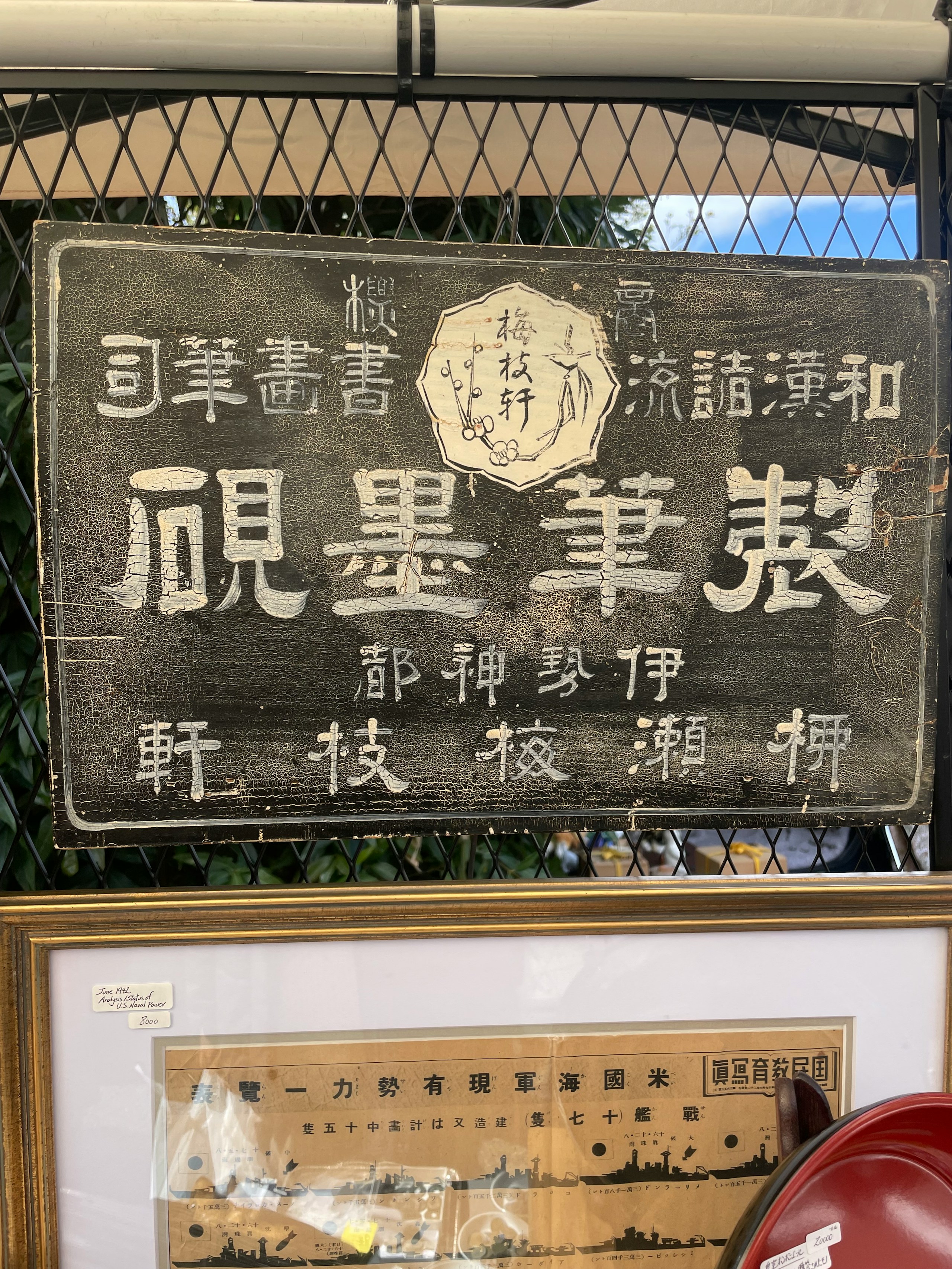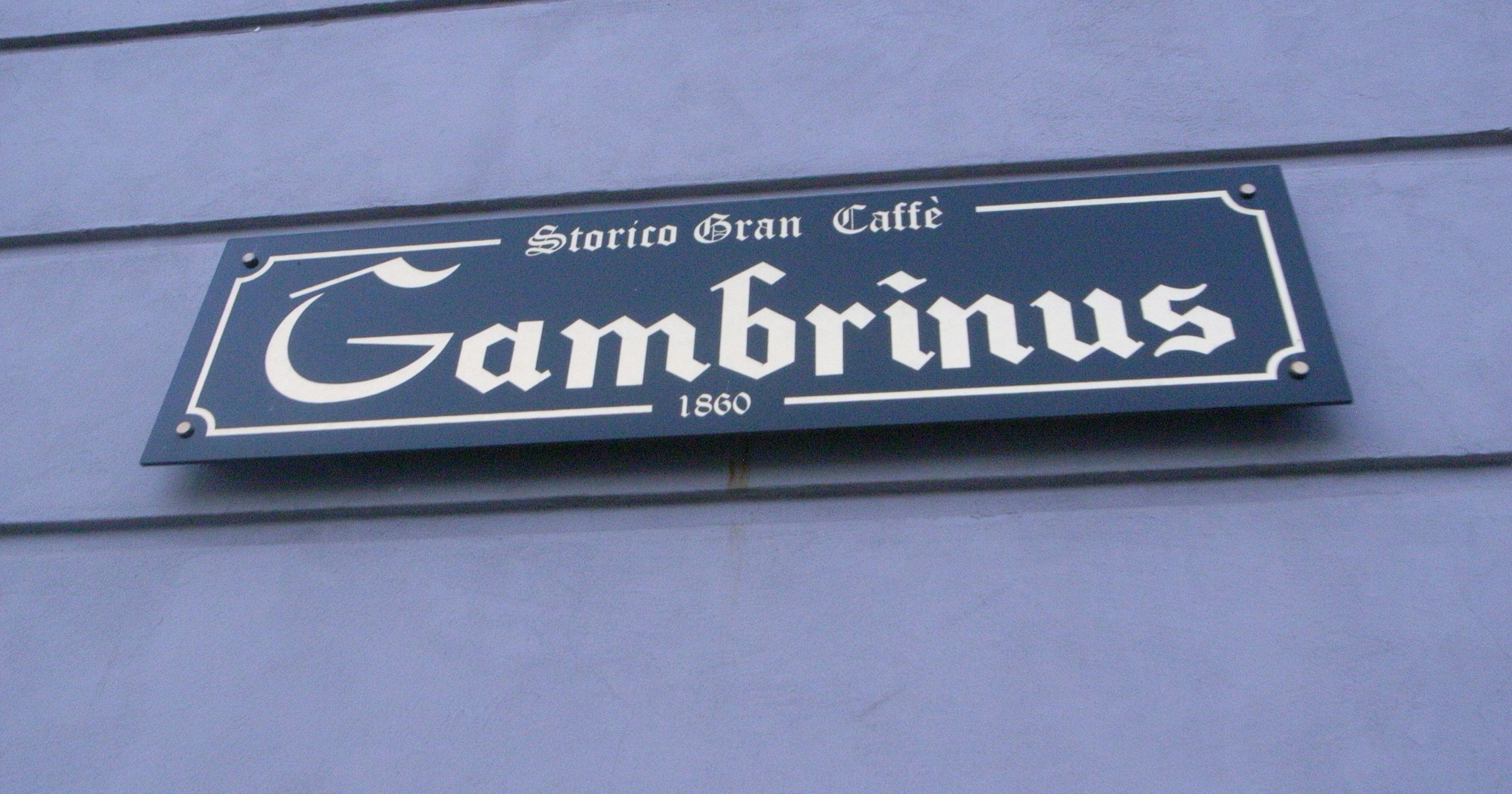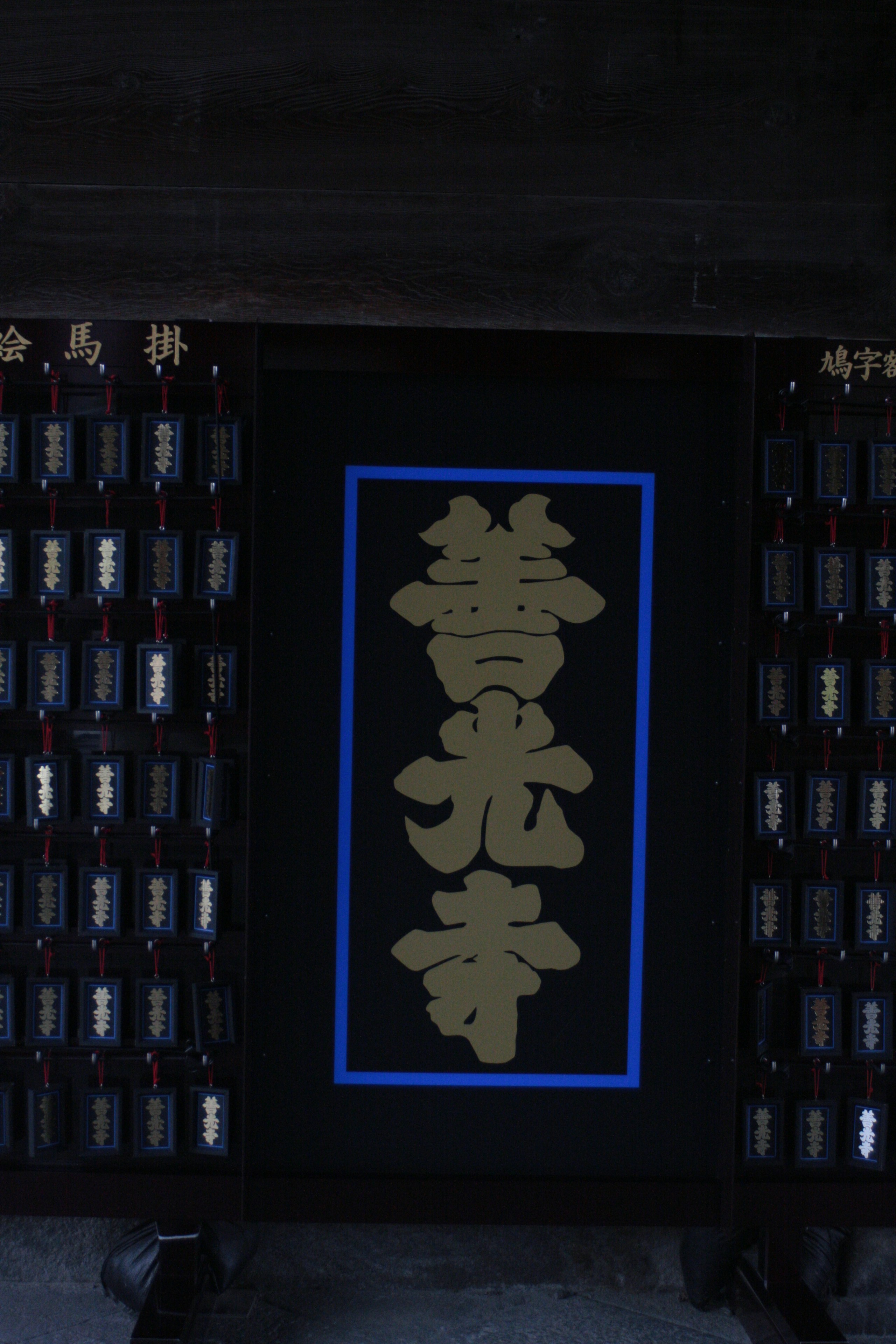
#フォント | Der Eindruck, den Schriften hinterlassen | Focus #59
Los geht's mit unserer Hashtag-Kampagne unter dem Motto 〈#フォント〉!
Es wird gesagt, dass es allein im Internet über 7000 verschiedene Schriftarten auf Japanisch gibt, und Schriften spielen eine große Rolle bei der Übermittlung von Informationen. Die Eigenschaften wie Dicke, Stil, Rundheit oder Kantigkeit variieren und werden je nach Art der Botschaft und Zielgruppe unterschiedlich eingesetzt.
Bitte posten Sie Fotos von Schriften in Ihrer Umgebung mit dem Hashtag 〈#フォント〉! Wir suchen nach einer breiten Palette von einzigartigen bis hin zu traditionellen Schriftarten!
Teilen Sie Ihre Kreationen mit #フォント